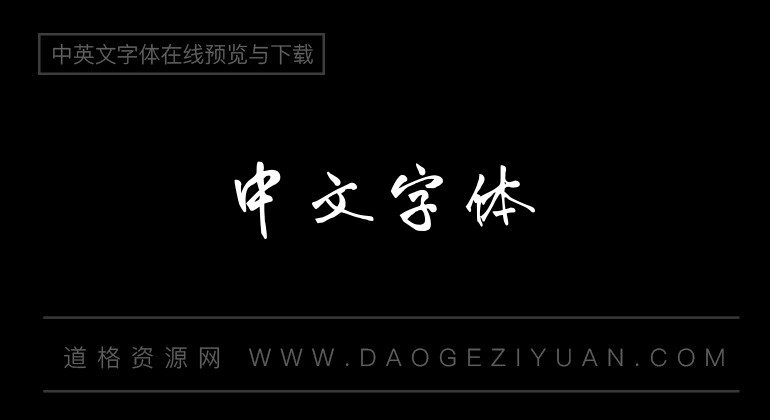
苏新诗鼠标行书简
苏新诗鼠标行书简是一款汉字书法字体,由苏州书法家苏新诗发明,以鼠标书写的方式创作而成。这款字体以书法的笔画为基础,融入了现代科技的元素,利用鼠标书写的方式,保留了传统的书法特点,并增加了更多的现代感,使汉字更加生动、灵动。苏新诗鼠标行书简的字体结构比较简洁,字形细腻,笔画更加柔和流畅,更具有表现力,使字体更加灵活、细腻、明快,能够更好地表达出文字的精神内涵。
苏新诗鼠标行书简是一款非常不错的手写艺术字体,具有很好的视觉感,适合于文化类的宣传设计、商业类品牌的广告和产品包装设计以及个性化文字排版等较多场景。